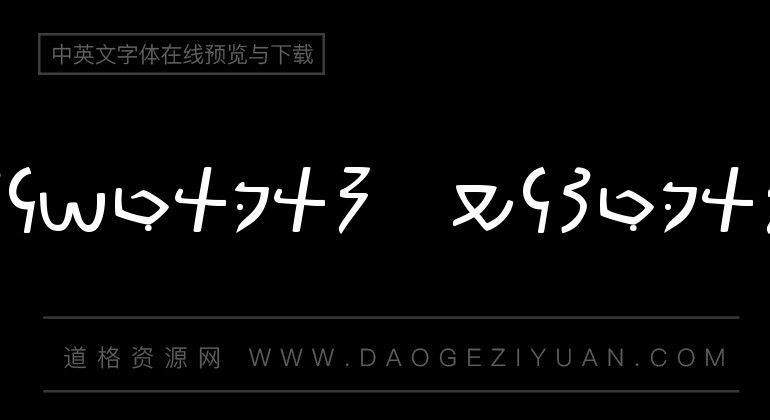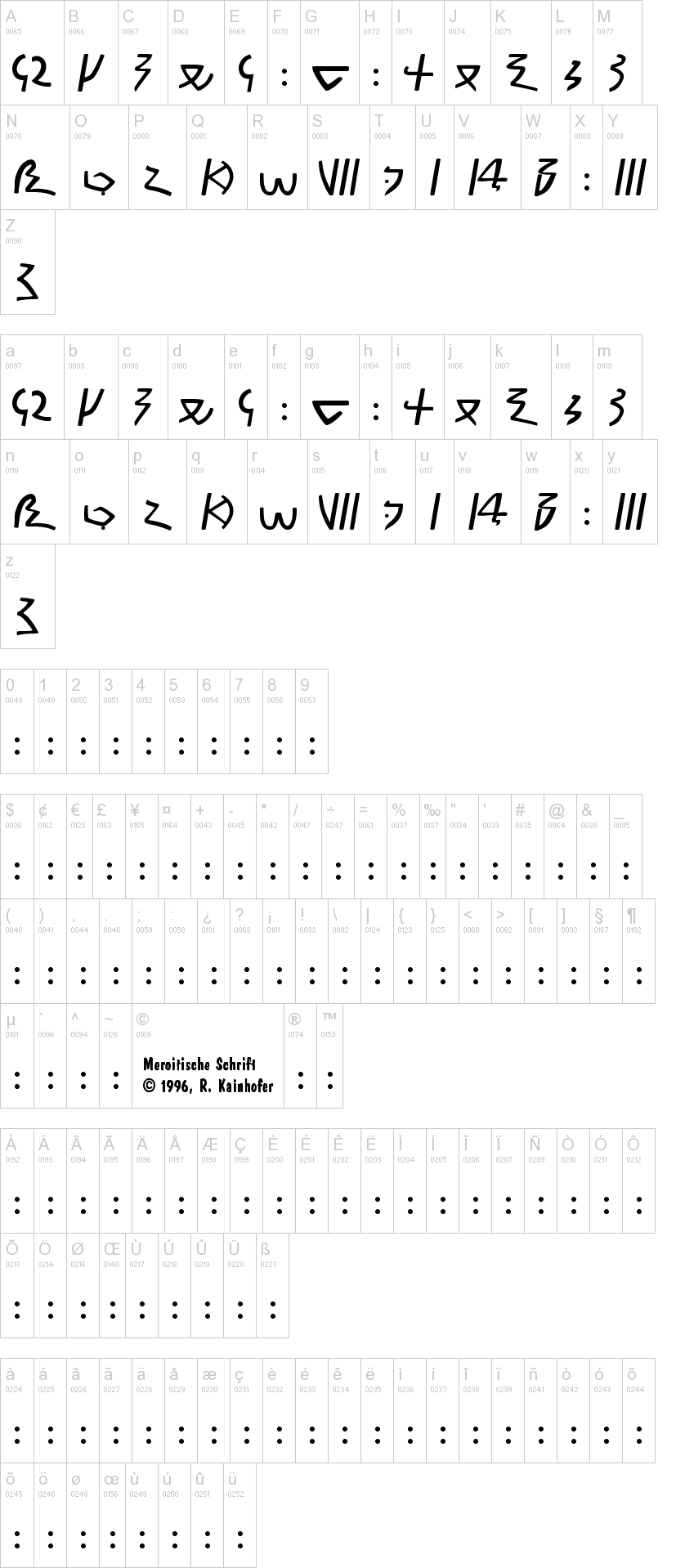
Meroitic Demotic
Meroitic Demotic是一种由古埃及文字发展而来的现代埃及文字字体,它是埃及文字学中一种重要的字体。它的名字来源于古埃及文字,以及古埃及文字中的一种古老文字,称为Meroitic,它是一种古老的埃及文字。Meroitic Demotic字体是在古埃及文字的基础上发展起来的,它的特点是字母的形状简单,字体的结构也比较简单,字体的表现也比较简洁,字体的字符也比较简单,它的字体结构也比较简单,字体的表现也比较简洁,字体的字符也比较简单。
Meroitic Demotic是一款非常不错的手写艺术字体,具有很好的视觉感,适合于文化类的宣传设计、商业类品牌的广告和产品包装设计以及个性化文字排版等较多场景。
Meroitic Demotic字符映射图